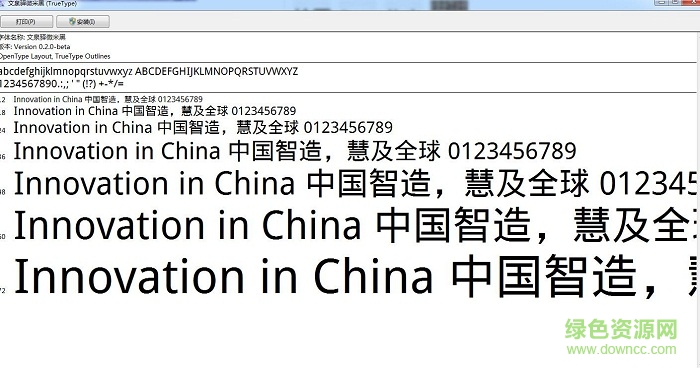
wenquanyimicroheimono
wenquanyimicrohei(文泉驛microhei)字體又叫文泉驛微米黑,是一款ttf格式的免費(fèi)字體,字型周正,大方得體,win7、win10等系統(tǒng)都可使用,歡迎大家免費(fèi)下載!
中文黑體字體特點(diǎn)
漢字的黑體是在現(xiàn)代印刷術(shù)傳入東方后依據(jù)西文無(wú)襯線體中的黑體所創(chuàng)造的。由于漢字筆劃多,小字的黑體清晰度較差,所以一開(kāi)始主要用于文章標(biāo)題,但隨著制字技術(shù)的精進(jìn),已有許多適用于內(nèi)文的黑體字型。
黑體字體類型
粗黑、超粗黑(特黑)、大黑、細(xì)黑、美黑、宋黑、水黑、藝黑、氈筆黑、平黑等類型。